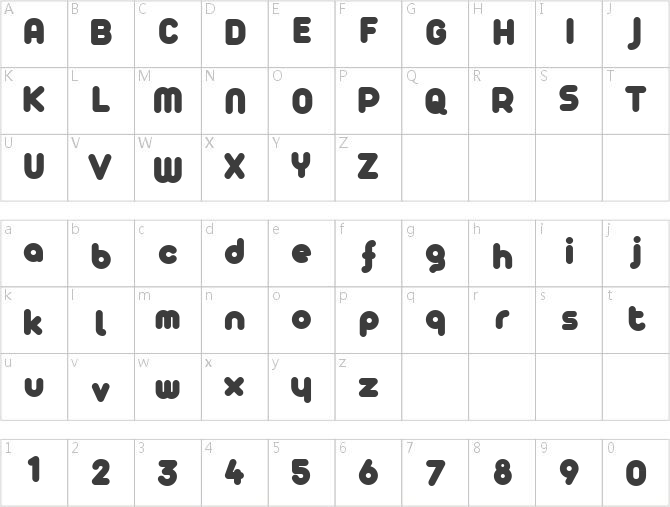
Arista Pro Fat
Arista Pro Fat介绍
Arista Pro Fat字体Arista-Pro-Fat字库是一款让人赏心悦目、百看不厌的英文字体,适合各类广告和产品包装设计应用,字体大小0.25MB,格式为ttf字体,上传用户是Apple,作者/版权方为Francesco Canovaro